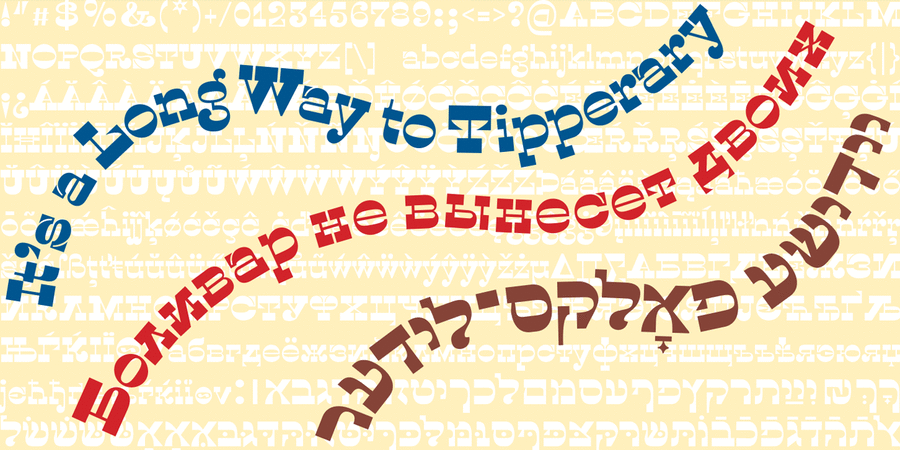
Caslon 1821 (1 шрифт)
Caslon1821 – це відроджений «італійський» шрифт студії Caslon & Livermore, 1821 рік. Цей шрифт швидко поширився по всій Європі та Америці. Він прийшов в Російську Імперію з Франції і став дуже популярним у 30-х роках XIX століття. Кириличні версії цього шрифту пропонували різні словолитни. У версії студії Apostrof є підтримка івриту (з голосними). Шрифт розробили Віктор Харик і Костянтин Головченко в 2014 році.
старомодний, ремісничий, самобутній, оригінальний, цікавий, характерний, дотепний, грайливий, іронічний, святковий, радісний, веселий, смішний, потішний, тісний, помітний, яскравий, виразний, артистичний, театральний, мультяшний, дитячий, химерний, демонстративний, багатий, експериментальний, стійкий, вінтажний, гострий, естетський, твердий, різкий, претензійний, екстравагантний, нонконформістський, богемний, амбітний, ностальгічний, олдскульний, важкий, дивний, старовинний, історичний, манірний, драматичний, мінливий, оманливий, епатажний, колючий